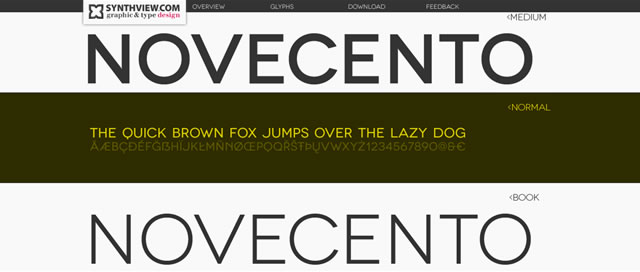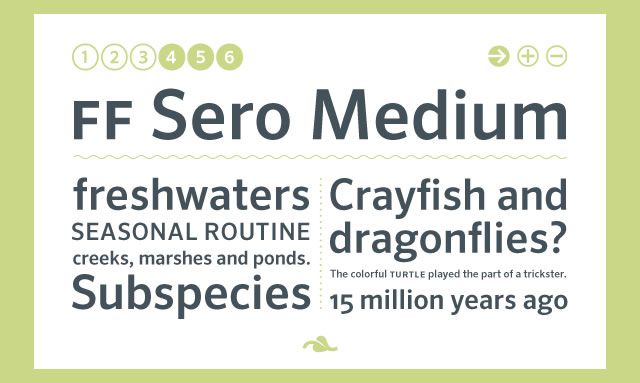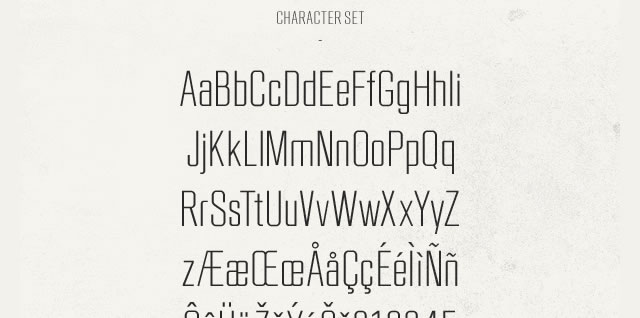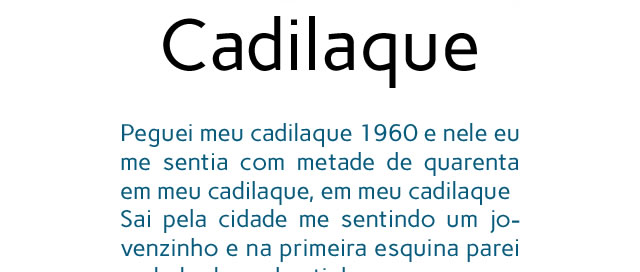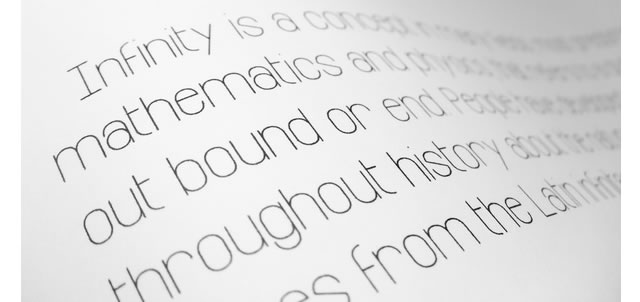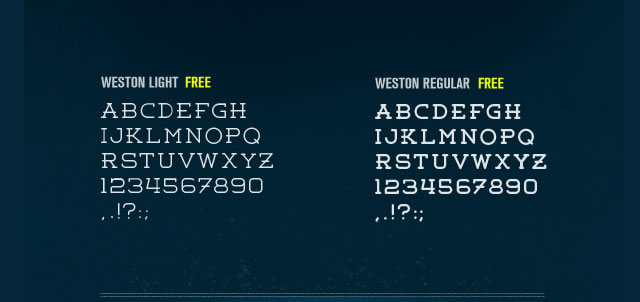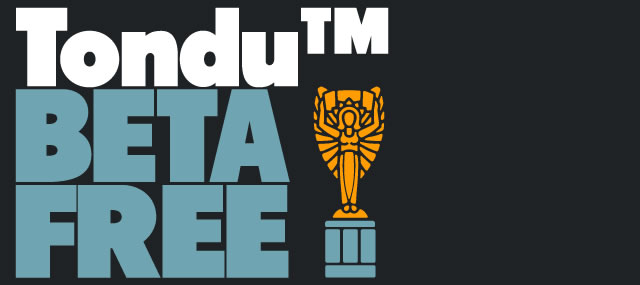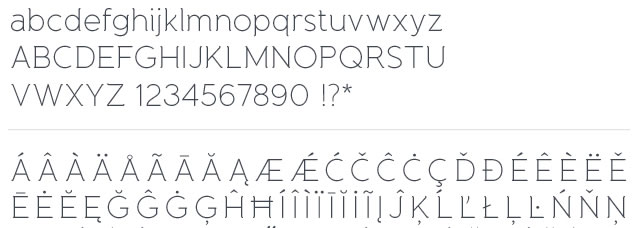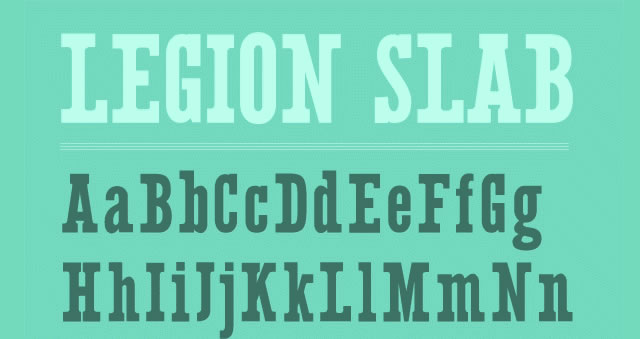
网页的header部分设计,可以说是网页整体设计中最重要的部分。而使用一个适合你自已网站风格的字体,又是重中之重。本文列举了20个适合网页头部使用的英文字体,简洁美丽大方。 Ostrich Sans (.ttf) Ostrich Sans Download Page Novecento (.otf) Novecento Download Page Sansus Webissimo (.otf) Sansus Webissimo Download Page FF Sero Medium (.otf) FF Sero Medium Download Page RBNo2 (.otf) RBNo2 Download Page Governor (.ttf) Governor Download Page Sheep Sans (.ttf) Sheep Sans Download Page Carme Sans-Serif (.otf & .ttf) Carme Sans-Serif Download Page Muli (.ttf) Muli Download Page@fontface Download Infinity (.ttf) Infinity Download Page Weston (.otf) Weston Download Page Quaver (.otf) Quaver Download Page Tondu Beta (.otf) Tondu Beta Download Page Banda Regular (.otf) Banda Regular Download Page Font FoglihtenFr02 (.otf) Font FoglihtenFr02 Download Page Claire Hand Light & Reular (.otf) Claire Hand Download Page Wisdom Script (.otf) Wisdom Script Download Page Legion Slab(.ttf) Legion Slab Download Page and finally… SD Helveticons (.ttf) SD Helveticons Download Page Loading... 网页的header部分设计,可以说是网页整体设计中最重要的部分。而使用一个适合你自已网站风格的字体,又是重中之重。本文列举了20个适合网页头部使用的英文字体,简洁美丽大方。<!--more--> <span class="external-link"><a class="no-external-link" href="http://www.theleagueofmoveabletype.com/fonts/18-ostrich-sans" target="_blank"><i data-feather="external-link"></i>Ostrich Sans</a></span> (.ttf) <span class="external-link"><a class="no-external-link" href="http://www.xiaoten.com/usr/uploads/2013/09/freefont_01.jpg" target="_blank"><i data-feather="external-link"></i><img class="attachment-full size-full" src="http://www.xiaoten.com/usr/uploads/2013/09/freefont_01.jpg" sizes="(max-width: 640px) 100vw, 640px" srcset="http://www.xiaoten.com/usr/uploads/2013/09/freefont_01-300x113.jpg 300w, http://www.xiaoten.com/usr/uploads/2013/09/freefont_01.jpg 640w" alt="freefont_01" width="640" height="240" style=""></a></span> <span class="external-link"><a class="no-external-link" href="http://www.theleagueofmoveabletype.com/fonts/18-ostrich-sans" target="_blank"><i data-feather="external-link"></i>Ostrich Sans Download Page</a></span> <span class="external-link"><a class="no-external-link" href="http://typography.synthview.com/" target="_blank"><i data-feather="external-link"></i>Novecento</a></span> (.otf) <span class="external-link"><a class="no-external-link" href="http://www.xiaoten.com/usr/uploads/2013/09/freefont_021.jpg" target="_blank"><i data-feather="external-link"></i><img class="attachment-full size-full" src="http://www.xiaoten.com/usr/uploads/2013/09/freefont_021.jpg" sizes="(max-width: 640px) 100vw, 640px" srcset="http://www.xiaoten.com/usr/uploads/2013/09/freefont_021-300x128.jpg 300w, http://www.xiaoten.com/usr/uploads/2013/09/freefont_021.jpg 640w" alt="freefont_021" width="640" height="272" style=""></a></span> <span class="external-link"><a class="no-external-link" href="http://typography.synthview.com/" target="_blank"><i data-feather="external-link"></i>Novecento Download Page</a></span> <span class="external-link"><a class="no-external-link" href="http://www.designcontest.com/webissimo-font/" target="_blank"><i data-feather="external-link"></i>Sansus Webissimo</a></span> (.otf) <span class="external-link"><a class="no-external-link" href="http://www.xiaoten.com/usr/uploads/2013/09/freefont_03.jpg" target="_blank"><i data-feather="external-link"></i><img class="attachment-full size-full" src="http://www.xiaoten.com/usr/uploads/2013/09/freefont_03.jpg" sizes="(max-width: 640px) 100vw, 640px" srcset="http://www.xiaoten.com/usr/uploads/2013/09/freefont_03-300x149.jpg 300w, http://www.xiaoten.com/usr/uploads/2013/09/freefont_03.jpg 640w" alt="freefont_03" width="640" height="318" style=""></a></span> <span class="external-link"><a class="no-external-link" href="http://www.designcontest.com/webissimo-font/" target="_blank"><i data-feather="external-link"></i>Sansus Webissimo Download Page</a></span> <span class="external-link"><a class="no-external-link" href="https://www.fontfont.com/free" target="_blank"><i data-feather="external-link"></i>FF Sero Medium</a></span> (.otf) <span class="external-link"><a class="no-external-link" href="http://www.xiaoten.com/usr/uploads/2013/09/freefont_04.jpg" target="_blank"><i data-feather="external-link"></i><img class="attachment-full size-full" src="http://www.xiaoten.com/usr/uploads/2013/09/freefont_04.jpg" sizes="(max-width: 640px) 100vw, 640px" srcset="http://www.xiaoten.com/usr/uploads/2013/09/freefont_04-300x180.jpg 300w, http://www.xiaoten.com/usr/uploads/2013/09/freefont_04.jpg 640w" alt="freefont_04" width="640" height="383" style=""></a></span> <span class="external-link"><a class="no-external-link" href="https://www.fontfont.com/free" target="_blank"><i data-feather="external-link"></i>FF Sero Medium Download Page</a></span> <span class="external-link"><a class="no-external-link" href="http://fontfabric.com/rbno2-free-font/" target="_blank"><i data-feather="external-link"></i>RBNo2</a></span> (.otf) <span class="external-link"><a class="no-external-link" href="http://www.xiaoten.com/usr/uploads/2013/09/freefont_05.jpg" target="_blank"><i data-feather="external-link"></i><img class="attachment-full size-full" src="http://www.xiaoten.com/usr/uploads/2013/09/freefont_05.jpg" sizes="(max-width: 640px) 100vw, 640px" srcset="http://www.xiaoten.com/usr/uploads/2013/09/freefont_05-300x149.jpg 300w, http://www.xiaoten.com/usr/uploads/2013/09/freefont_05.jpg 640w" alt="freefont_05" width="640" height="318" style=""></a></span> <span class="external-link"><a class="no-external-link" href="http://fontfabric.com/rbno2-free-font/" target="_blank"><i data-feather="external-link"></i>RBNo2 Download Page</a></span> <span class="external-link"><a class="no-external-link" href="http://www.losttype.com/font/?name=governor" target="_blank"><i data-feather="external-link"></i>Governor</a></span> (.ttf) <span class="external-link"><a class="no-external-link" href="http://www.xiaoten.com/usr/uploads/2013/09/freefont_06.jpg" target="_blank"><i data-feather="external-link"></i><img class="attachment-full size-full" src="http://www.xiaoten.com/usr/uploads/2013/09/freefont_06.jpg" sizes="(max-width: 640px) 100vw, 640px" srcset="http://www.xiaoten.com/usr/uploads/2013/09/freefont_06-300x141.jpg 300w, http://www.xiaoten.com/usr/uploads/2013/09/freefont_06.jpg 640w" alt="freefont_06" width="640" height="300" style=""></a></span> <span class="external-link"><a class="no-external-link" href="http://www.losttype.com/font/?name=governor" target="_blank"><i data-feather="external-link"></i>Governor Download Page</a></span> <span class="external-link"><a class="no-external-link" href="http://www.dafont.com/sheep-sans.font" target="_blank"><i data-feather="external-link"></i>Sheep Sans</a></span> (.ttf) <span class="external-link"><a class="no-external-link" href="http://www.xiaoten.com/usr/uploads/2013/09/freefont_07.jpg" target="_blank"><i data-feather="external-link"></i><img class="attachment-full size-full" src="http://www.xiaoten.com/usr/uploads/2013/09/freefont_07.jpg" sizes="(max-width: 640px) 100vw, 640px" srcset="http://www.xiaoten.com/usr/uploads/2013/09/freefont_07-300x128.jpg 300w, http://www.xiaoten.com/usr/uploads/2013/09/freefont_07.jpg 640w" alt="freefont_07" width="640" height="272" style=""></a></span> <span class="external-link"><a class="no-external-link" href="http://www.dafont.com/sheep-sans.font" target="_blank"><i data-feather="external-link"></i>Sheep Sans Download Page</a></span> <span class="external-link"><a class="no-external-link" href="http://www.ipanemagrafica.com/carme/" target="_blank"><i data-feather="external-link"></i>Carme Sans-Serif</a></span> (.otf & .ttf) <span class="external-link"><a class="no-external-link" href="http://www.xiaoten.com/usr/uploads/2013/09/freefont_08.jpg" target="_blank"><i data-feather="external-link"></i><img class="attachment-full size-full" src="http://www.xiaoten.com/usr/uploads/2013/09/freefont_08.jpg" sizes="(max-width: 640px) 100vw, 640px" srcset="http://www.xiaoten.com/usr/uploads/2013/09/freefont_08-300x128.jpg 300w, http://www.xiaoten.com/usr/uploads/2013/09/freefont_08.jpg 640w" alt="freefont_08" width="640" height="272" style=""></a></span> <span class="external-link"><a class="no-external-link" href="http://www.ipanemagrafica.com/carme/" target="_blank"><i data-feather="external-link"></i>Carme Sans-Serif Download Page</a></span> <span class="external-link"><a class="no-external-link" href="http://www.fontsquirrel.com/fonts/muli" target="_blank"><i data-feather="external-link"></i>Muli</a></span> (.ttf) <span class="external-link"><a class="no-external-link" href="http://www.xiaoten.com/usr/uploads/2013/09/freefont_09.jpg" target="_blank"><i data-feather="external-link"></i><img class="attachment-full size-full" src="http://www.xiaoten.com/usr/uploads/2013/09/freefont_09.jpg" sizes="(max-width: 640px) 100vw, 640px" srcset="http://www.xiaoten.com/usr/uploads/2013/09/freefont_09-300x142.jpg 300w, http://www.xiaoten.com/usr/uploads/2013/09/freefont_09.jpg 640w" alt="freefont_09" width="640" height="302" style=""></a></span> <span class="external-link"><a class="no-external-link" href="http://www.fontsquirrel.com/fonts/muli" target="_blank"><i data-feather="external-link"></i>Muli Download Page</a></span><span class="external-link"><a class="no-external-link" href="http://www.fontsquirrel.com/fonts/muli" target="_blank"><i data-feather="external-link"></i>@fontface Download</a></span> <span class="external-link"><a class="no-external-link" href="http://www.behance.net/gallery/Infinity/1126535" target="_blank"><i data-feather="external-link"></i>Infinity</a></span> (.ttf) <span class="external-link"><a class="no-external-link" href="http://www.xiaoten.com/usr/uploads/2013/09/freefont_10.jpg" target="_blank"><i data-feather="external-link"></i><img class="attachment-full size-full" src="http://www.xiaoten.com/usr/uploads/2013/09/freefont_10.jpg" sizes="(max-width: 640px) 100vw, 640px" srcset="http://www.xiaoten.com/usr/uploads/2013/09/freefont_10-300x142.jpg 300w, http://www.xiaoten.com/usr/uploads/2013/09/freefont_10.jpg 640w" alt="freefont_10" width="640" height="302" style=""></a></span> <span class="external-link"><a class="no-external-link" href="http://www.behance.net/gallery/Infinity/1126535" target="_blank"><i data-feather="external-link"></i>Infinity Download Page</a></span> <span class="external-link"><a class="no-external-link" href="http://fontfabric.com/weston-free-font/" target="_blank"><i data-feather="external-link"></i>Weston</a></span> (.otf) <span class="external-link"><a class="no-external-link" href="http://www.xiaoten.com/usr/uploads/2013/09/freefont_11.jpg" target="_blank"><i data-feather="external-link"></i><img class="attachment-full size-full" src="http://www.xiaoten.com/usr/uploads/2013/09/freefont_11.jpg" sizes="(max-width: 640px) 100vw, 640px" srcset="http://www.xiaoten.com/usr/uploads/2013/09/freefont_11-300x142.jpg 300w, http://www.xiaoten.com/usr/uploads/2013/09/freefont_11.jpg 640w" alt="freefont_11" width="640" height="302" style=""></a></span> <span class="external-link"><a class="no-external-link" href="http://fontfabric.com/weston-free-font/" target="_blank"><i data-feather="external-link"></i>Weston Download Page</a></span> <span class="external-link"><a class="no-external-link" href="http://www.losttype.com/font/?name=quaver" target="_blank"><i data-feather="external-link"></i>Quaver</a></span> (.otf) <span class="external-link"><a class="no-external-link" href="http://www.xiaoten.com/usr/uploads/2013/09/freefont_12.jpg" target="_blank"><i data-feather="external-link"></i><img class="attachment-full size-full" src="http://www.xiaoten.com/usr/uploads/2013/09/freefont_12.jpg" sizes="(max-width: 640px) 100vw, 640px" srcset="http://www.xiaoten.com/usr/uploads/2013/09/freefont_12-300x134.jpg 300w, http://www.xiaoten.com/usr/uploads/2013/09/freefont_12.jpg 640w" alt="freefont_12" width="640" height="285" style=""></a></span> <span class="external-link"><a class="no-external-link" href="http://www.losttype.com/font/?name=quaver" target="_blank"><i data-feather="external-link"></i>Quaver Download Page</a></span> <span class="external-link"><a class="no-external-link" href="http://www.thenorthernblock.co.uk/tondu_beta.htm" target="_blank"><i data-feather="external-link"></i>Tondu Beta</a></span> (.otf) <span class="external-link"><a class="no-external-link" href="http://www.xiaoten.com/usr/uploads/2013/09/freefont_13.jpg" target="_blank"><i data-feather="external-link"></i><img class="attachment-full size-full" src="http://www.xiaoten.com/usr/uploads/2013/09/freefont_13.jpg" sizes="(max-width: 640px) 100vw, 640px" srcset="http://www.xiaoten.com/usr/uploads/2013/09/freefont_13-300x134.jpg 300w, http://www.xiaoten.com/usr/uploads/2013/09/freefont_13.jpg 640w" alt="freefont_13" width="640" height="285" style=""></a></span> <span class="external-link"><a class="no-external-link" href="http://www.thenorthernblock.co.uk/tondu_beta.htm" target="_blank"><i data-feather="external-link"></i>Tondu Beta Download Page</a></span> <span class="external-link"><a class="no-external-link" href="http://www.typedepot.com/banda" target="_blank"><i data-feather="external-link"></i>Banda Regular</a></span> (.otf) <span class="external-link"><a class="no-external-link" href="http://www.xiaoten.com/usr/uploads/2013/09/freefont_14.jpg" target="_blank"><i data-feather="external-link"></i><img class="attachment-full size-full" src="http://www.xiaoten.com/usr/uploads/2013/09/freefont_14.jpg" sizes="(max-width: 640px) 100vw, 640px" srcset="http://www.xiaoten.com/usr/uploads/2013/09/freefont_14-300x107.jpg 300w, http://www.xiaoten.com/usr/uploads/2013/09/freefont_14.jpg 640w" alt="freefont_14" width="640" height="228" style=""></a></span> <span class="external-link"><a class="no-external-link" href="http://www.typedepot.com/banda" target="_blank"><i data-feather="external-link"></i>Banda Regular Download Page</a></span> <span class="external-link"><a class="no-external-link" href="http://www.glukfonts.pl/font.php?l=en&font=FoglihtenFr02" target="_blank"><i data-feather="external-link"></i>Font FoglihtenFr02</a></span> (.otf) <span class="external-link"><a class="no-external-link" href="http://www.xiaoten.com/usr/uploads/2013/09/freefont_15.jpg" target="_blank"><i data-feather="external-link"></i><img class="attachment-full size-full" src="http://www.xiaoten.com/usr/uploads/2013/09/freefont_15.jpg" sizes="(max-width: 640px) 100vw, 640px" srcset="http://www.xiaoten.com/usr/uploads/2013/09/freefont_15-300x115.jpg 300w, http://www.xiaoten.com/usr/uploads/2013/09/freefont_15.jpg 640w" alt="freefont_15" width="640" height="246" style=""></a></span> <span class="external-link"><a class="no-external-link" href="http://www.glukfonts.pl/font.php?l=en&font=FoglihtenFr02" target="_blank"><i data-feather="external-link"></i>Font FoglihtenFr02 Download Page</a></span> <span class="external-link"><a class="no-external-link" href="http://www.teamscope.com.au/claire-hand-the-new-team-scope-font/" target="_blank"><i data-feather="external-link"></i>Claire Hand Light & Reular</a></span> (.otf) <span class="external-link"><a class="no-external-link" href="http://www.xiaoten.com/usr/uploads/2013/09/freefont_16.jpg" target="_blank"><i data-feather="external-link"></i><img class="attachment-full size-full" src="http://www.xiaoten.com/usr/uploads/2013/09/freefont_16.jpg" sizes="(max-width: 640px) 100vw, 640px" srcset="http://www.xiaoten.com/usr/uploads/2013/09/freefont_16-300x159.jpg 300w, http://www.xiaoten.com/usr/uploads/2013/09/freefont_16.jpg 640w" alt="freefont_16" width="640" height="340" style=""></a></span> <span class="external-link"><a class="no-external-link" href="http://www.teamscope.com.au/claire-hand-the-new-team-scope-font/" target="_blank"><i data-feather="external-link"></i>Claire Hand Download Page</a></span> <span class="external-link"><a class="no-external-link" href="http://www.losttype.com/font/?name=wisdom%20script" target="_blank"><i data-feather="external-link"></i>Wisdom Script</a></span> (.otf) <span class="external-link"><a class="no-external-link" href="http://www.xiaoten.com/usr/uploads/2013/09/freefont_17.jpg" target="_blank"><i data-feather="external-link"></i><img class="attachment-full size-full" src="http://www.xiaoten.com/usr/uploads/2013/09/freefont_17.jpg" sizes="(max-width: 640px) 100vw, 640px" srcset="http://www.xiaoten.com/usr/uploads/2013/09/freefont_17-300x141.jpg 300w, http://www.xiaoten.com/usr/uploads/2013/09/freefont_17.jpg 640w" alt="freefont_17" width="640" height="300" style=""></a></span> <span class="external-link"><a class="no-external-link" href="http://www.losttype.com/font/?name=wisdom%20script" target="_blank"><i data-feather="external-link"></i>Wisdom Script Download Page</a></span> <span class="external-link"><a class="no-external-link" href="http://www.behance.net/gallery/Legion-Slab-Typeface/1633237" target="_blank"><i data-feather="external-link"></i>Legion Slab</a></span>(.ttf) <span class="external-link"><a class="no-external-link" href="http://www.xiaoten.com/usr/uploads/2013/09/freefont_18.jpg" target="_blank"><i data-feather="external-link"></i><img class="attachment-full size-full" src="http://www.xiaoten.com/usr/uploads/2013/09/freefont_18.jpg" sizes="(max-width: 640px) 100vw, 640px" srcset="http://www.xiaoten.com/usr/uploads/2013/09/freefont_18-300x159.jpg 300w, http://www.xiaoten.com/usr/uploads/2013/09/freefont_18.jpg 640w" alt="freefont_18" width="640" height="339" style=""></a></span> <span class="external-link"><a class="no-external-link" href="http://www.behance.net/gallery/Legion-Slab-Typeface/1633237" target="_blank"><i data-feather="external-link"></i>Legion Slab Download Page</a></span> and finally… <span class="external-link"><a class="no-external-link" href="http://www.fonts2u.com/sd-helveticons-demo.font" target="_blank"><i data-feather="external-link"></i>SD Helveticons</a></span> (.ttf) <span class="external-link"><a class="no-external-link" href="http://www.xiaoten.com/usr/uploads/2013/09/freefont_20.jpg" target="_blank"><i data-feather="external-link"></i><img class="attachment-full size-full" src="http://www.xiaoten.com/usr/uploads/2013/09/freefont_20.jpg" sizes="(max-width: 640px) 100vw, 640px" srcset="http://www.xiaoten.com/usr/uploads/2013/09/freefont_20-300x159.jpg 300w, http://www.xiaoten.com/usr/uploads/2013/09/freefont_20.jpg 640w" alt="freefont_20" width="640" height="339" style=""></a></span> <span class="external-link"><a class="no-external-link" href="http://www.fonts2u.com/sd-helveticons-demo.font" target="_blank"><i data-feather="external-link"></i>SD Helveticons Download Page</a></span> © 允许规范转载 赞 如果觉得我的文章对你有用,请随意赞赏